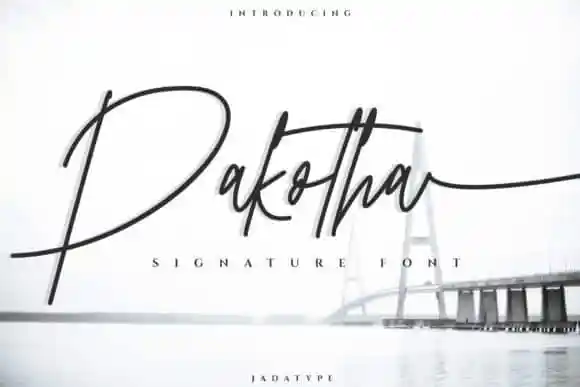
Pakotha Handwritten Font – Download Grátis
A PAKOTha Handwritten Font é uma inovação no mundo dos tipos de caracteres que vem com uma rica mistura de elegância e autenticidade. Criada pelo designer jadatype, ela oferece um estilo único e contemporâneo, além de alternativas gráficas belamente pensadas para permitir que você crie design tão impressionantes quanto possa imaginar. Seu formato monoline é tanto para assinaturas sofisticadas como para textos mais informais, adaptando-se perfeitamente a um vasto leque de aplicativos. Com acesso fácil a todos os símbolos e swashes graças à sua codificação PUA, essa fonte se torna uma verdadeira ferramenta versátil que pode revolucionar seu modo de trabalhar com texto. Seja você um profissional criativo ou um designer casual, este tipo de escrita manuscrita lhe proporcionará uma linguagem única para destacar suas criações. A PAKOTha Handwritten é a escolha perfeita para quem deseja deixar seu rastro no mundo dos designs digitais com um estilo autêntico e sofisticado. Descubra o poder dessa fonte em sua próxima obra prima!